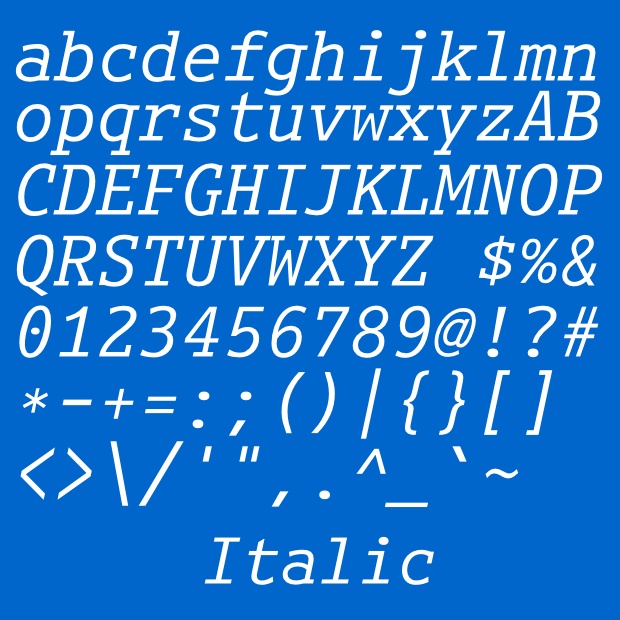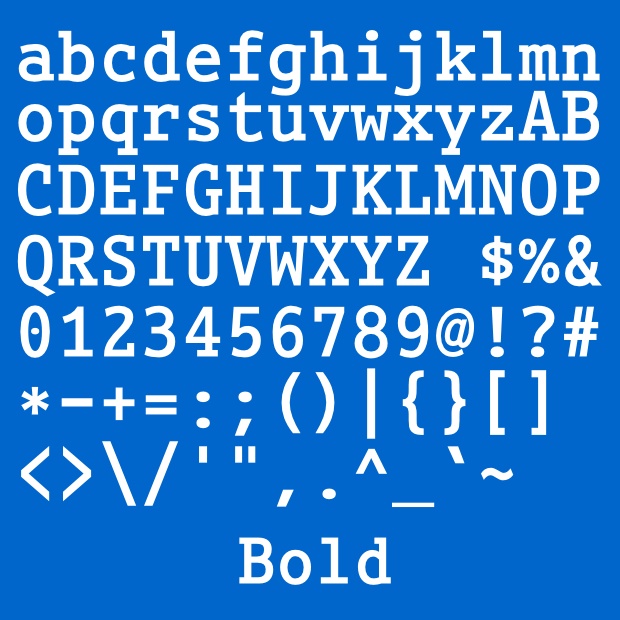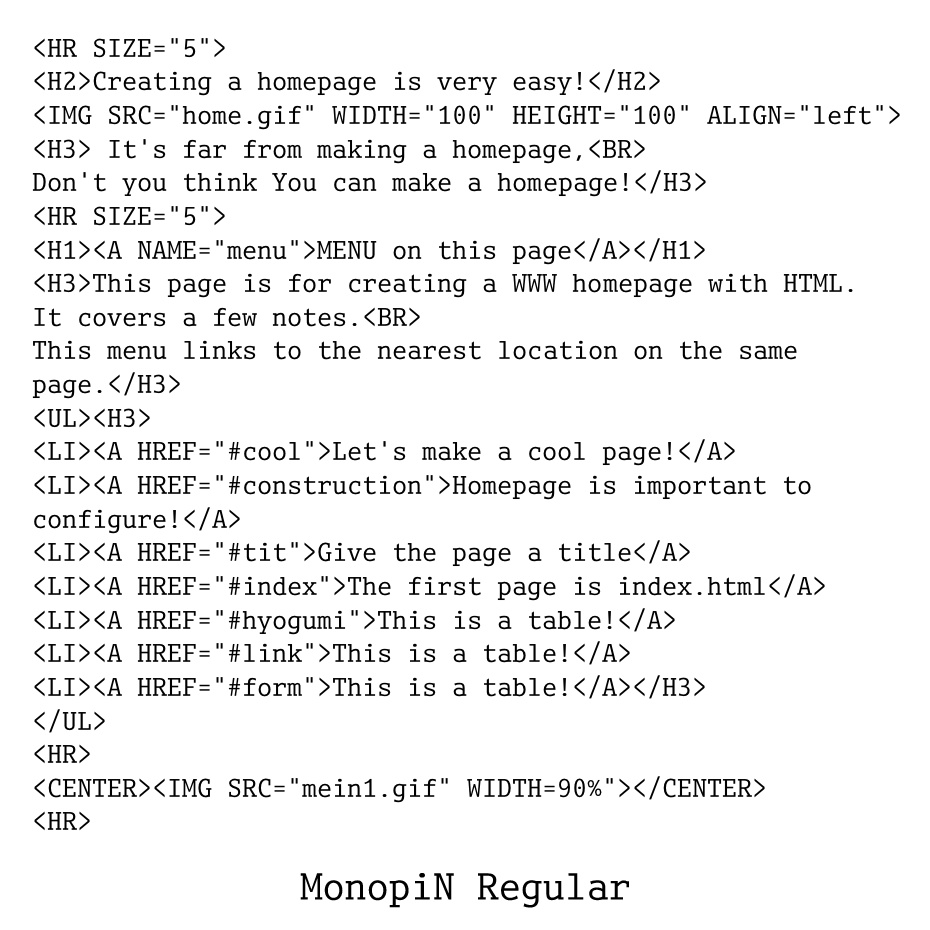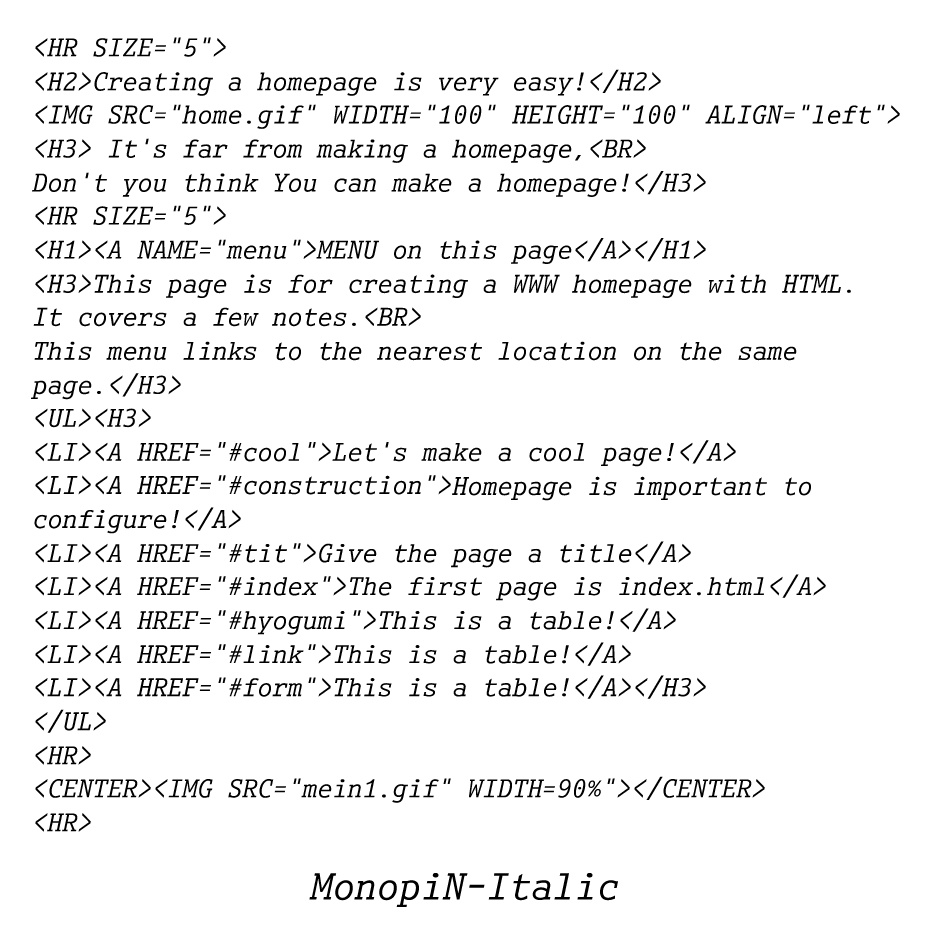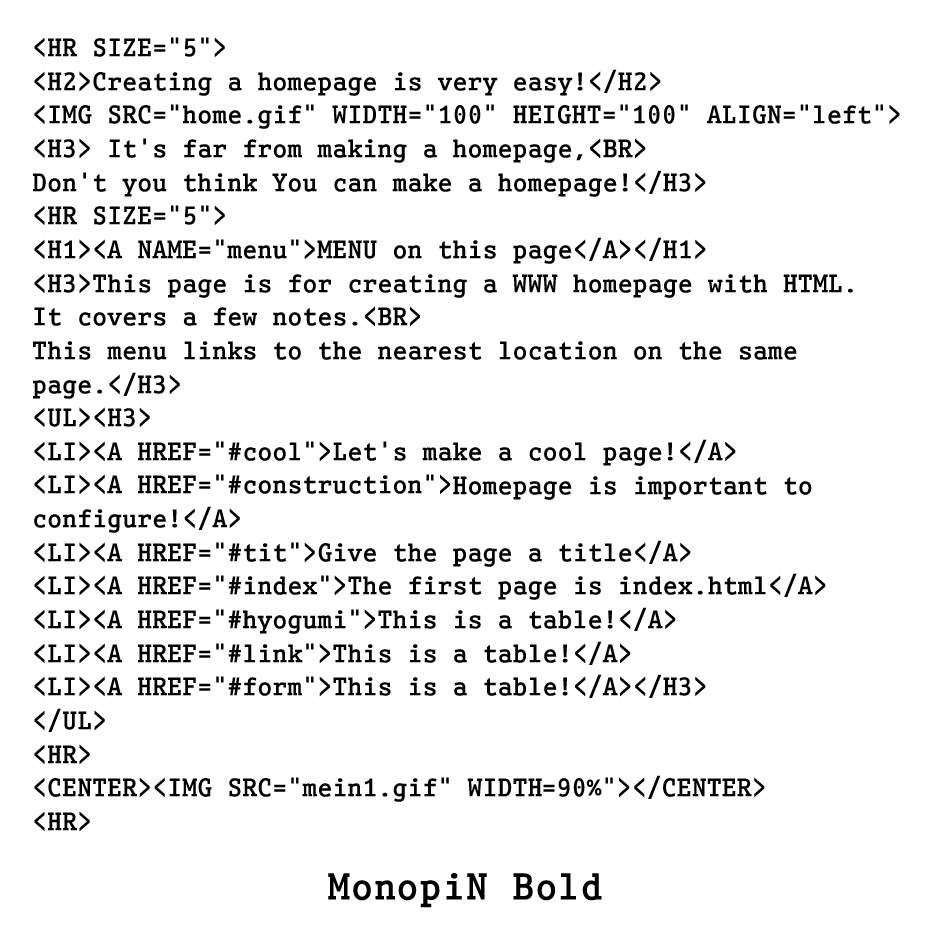
プログラミング用に特化した欧文TrueTypeフォントです。
●この商品には、Regular/Italic/Boldの3つのフォントが入っています。
◎ASCII文字「94文字」だけしか含まれていません。
◎各文字の横幅は全角の63%です(50%ではありません)。
◎円マーク「¥」は表示せずに、バックスラッシュ「\」で表示します。